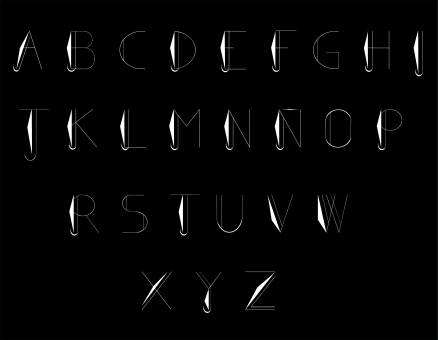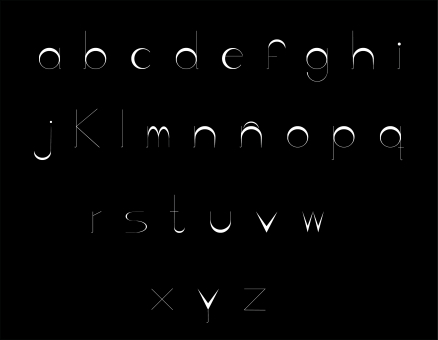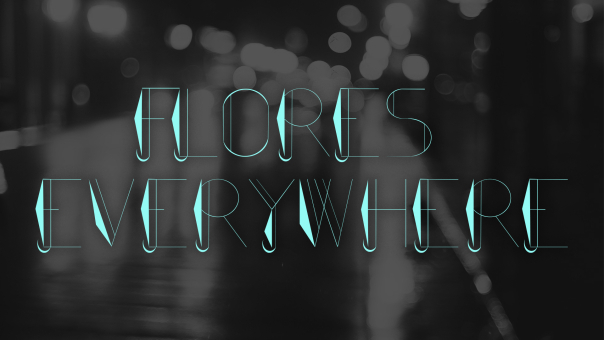
Ferchongo Elegant
Es una fuente que se recomienda para ilustraciones y posters.
Designer: Fernanda Barajas Aguilar
Publisher: Fernanda Barajas Aguilar